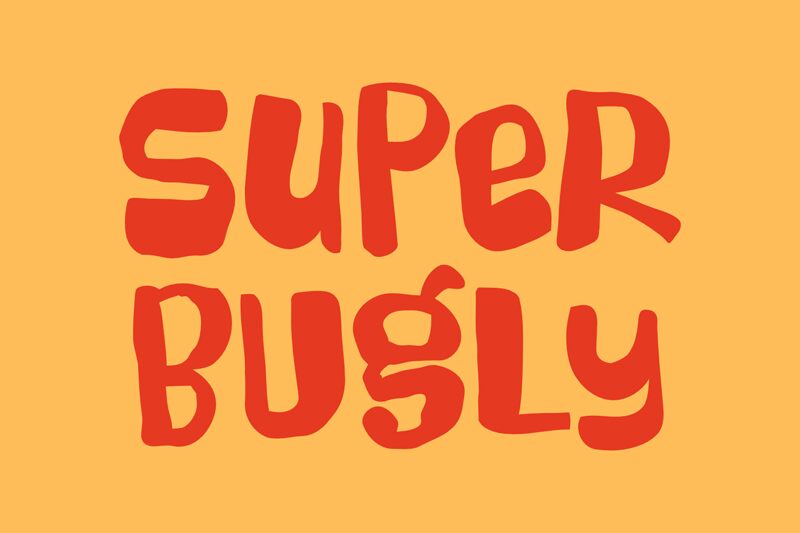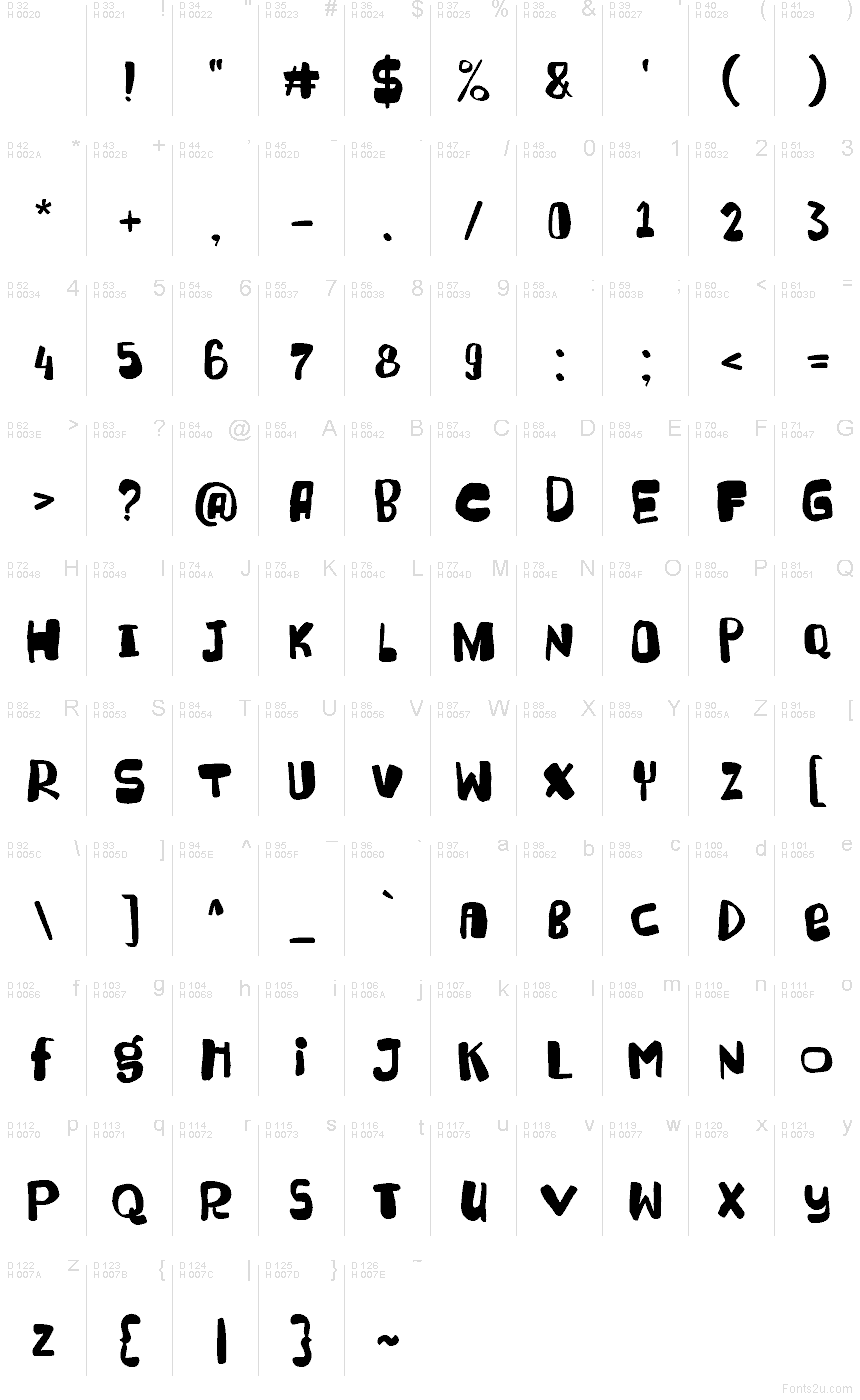
Super Bugly Regular
Super Bugly هو خط عرض مجاني بأسلوب الكرتون، يتميز بصور ظلية منتفخة وغير منتظمة تجعل الحروف تبدو ناعمة ومطاطية وغير متوازنة قليلاً. تتمدد الأشكال المستديرة وتنكمش من حرف إلى آخر، مما يمنح التصميم إيقاعاً حيوياً يبدو وكأنه لافتة رسوم متحركة مرسومة يدوياً أكثر من كونه نمط عرض هندسي مرتب.
تتناسب هذه الأشكال الحرة والعفوية تماماً مع ملصقات الأطفال، وعبوات الوجبات الخفيفة، وعناوين الكوميكس، وأسماء الألعاب، ودعوات الحفلات التي تحتاج إلى لمسة مرحة. تحقق الشعارات القصيرة والعناوين الكبيرة أقصى استفادة من هذا الخط، حيث تخلق الخطوط الخارجية غير المنتظمة ملمساً حيوياً يمنع الكلمات البسيطة من أن تبدو مسطحة أو رسمية للغاية.